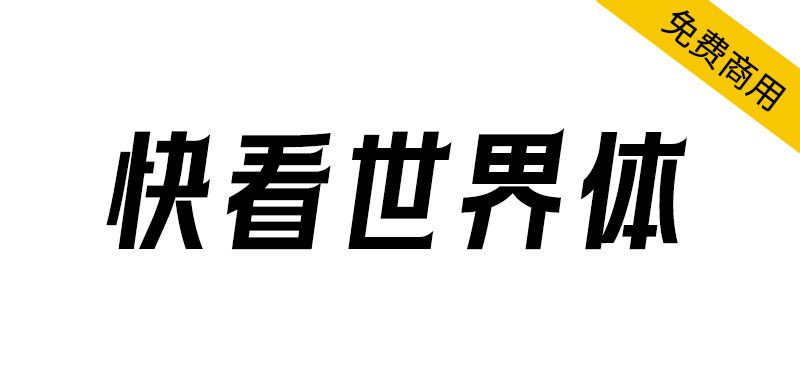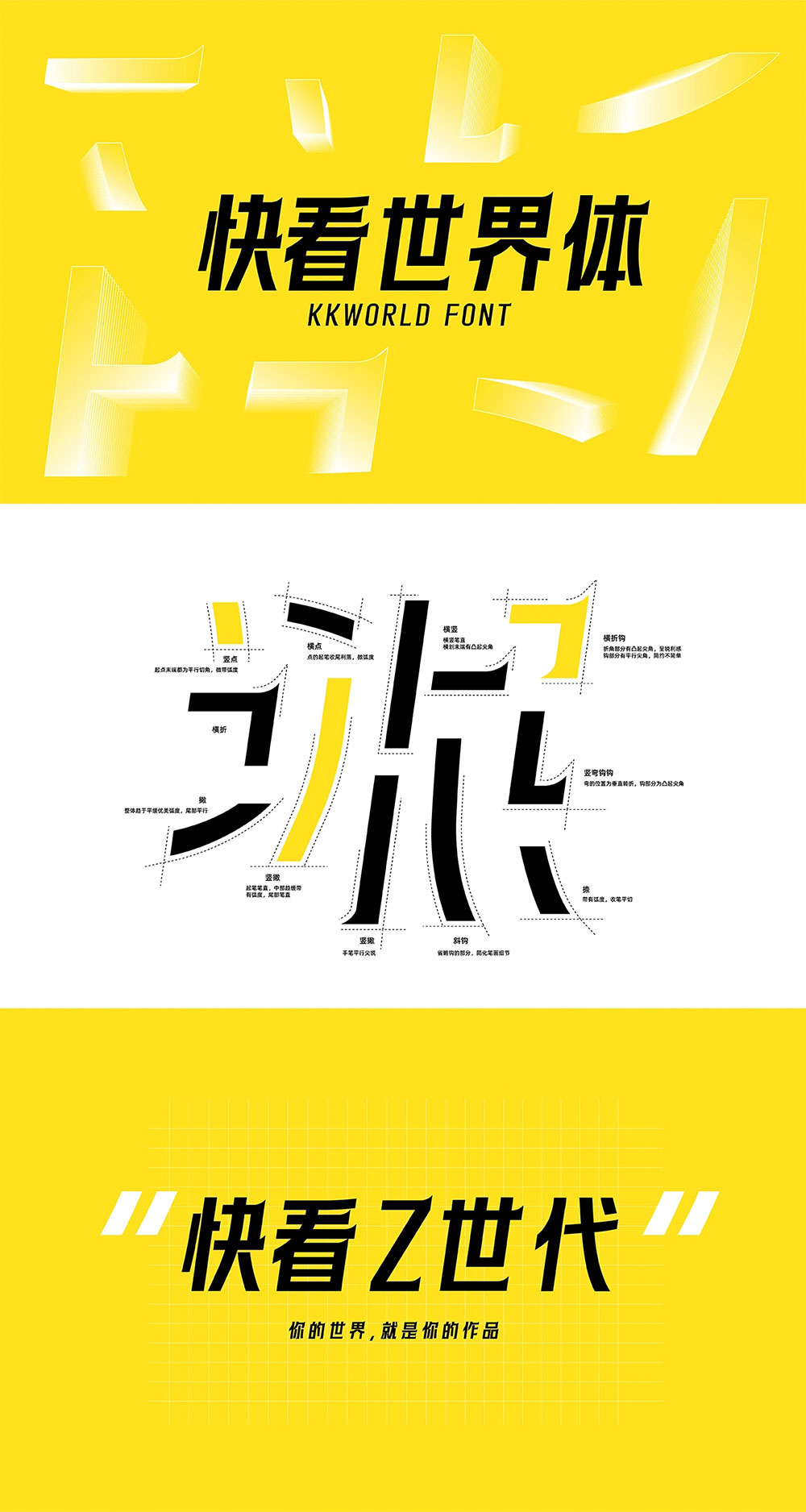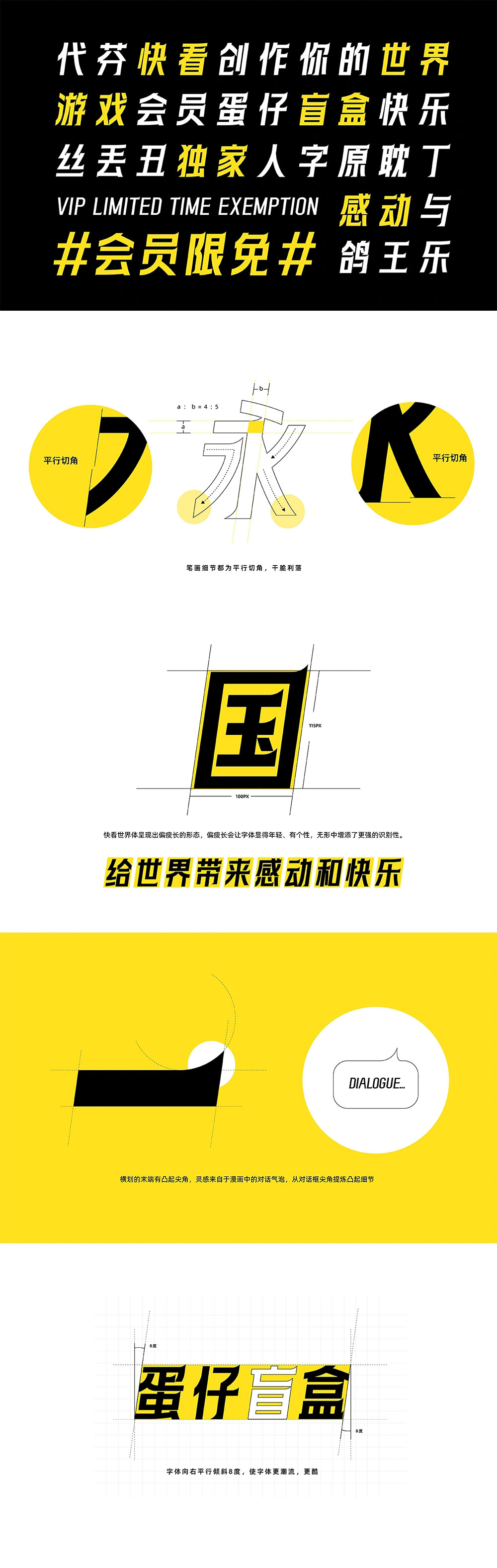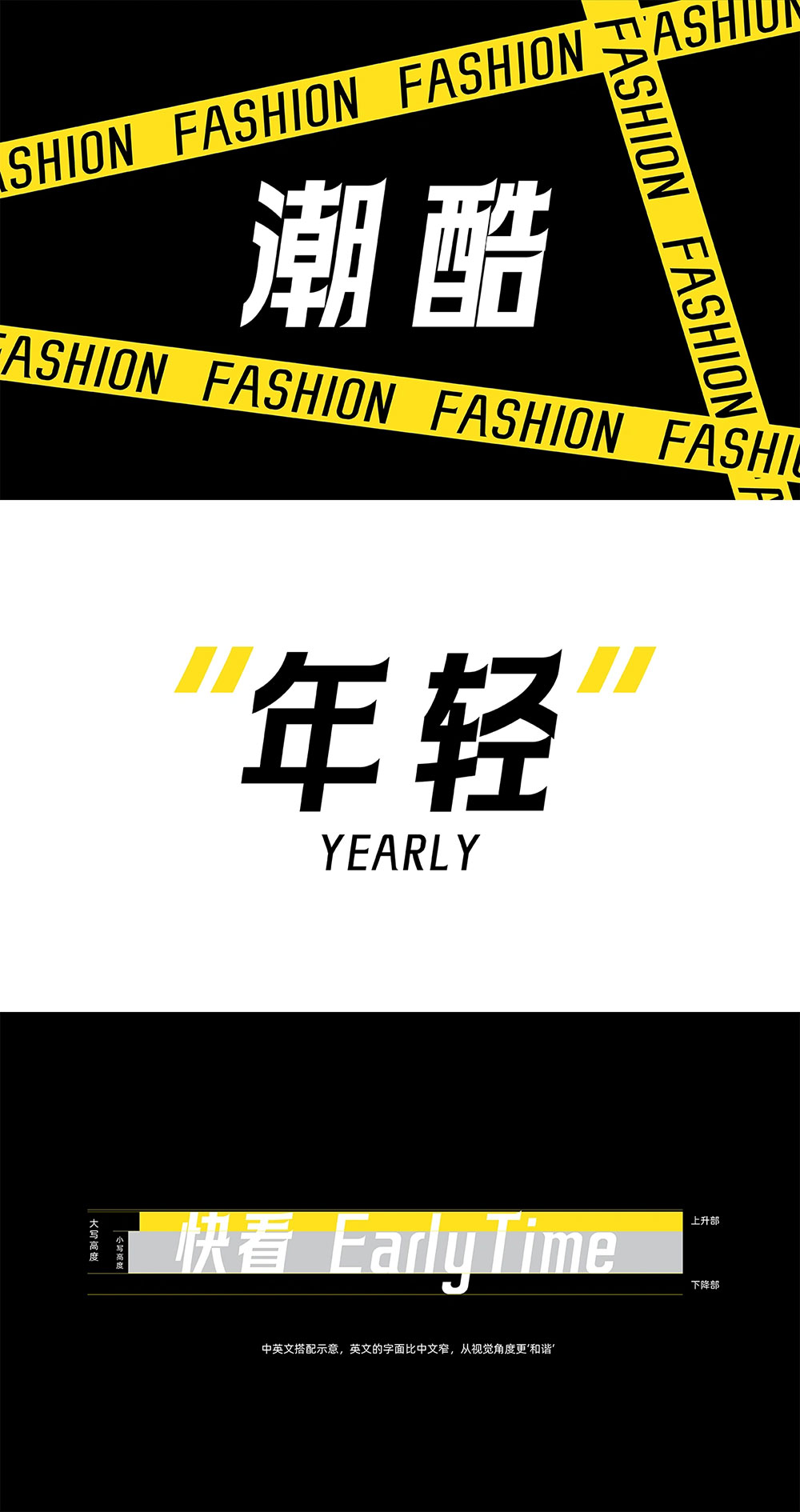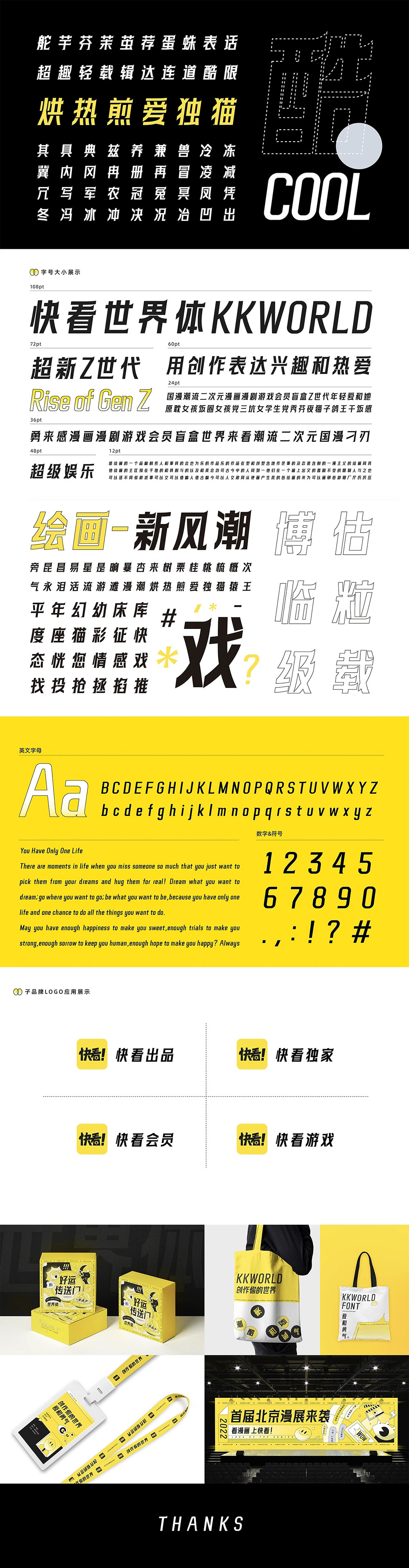
这款字是我第一款从设计-封装-测试全部自己完成的字库快看世界体由快看KKDC出品,字体设计以漫画中的对话框元素为起点,融入快看ACGN文化,年轻潮流,大胆有态度。
字体特点末端尖角,中宫外扩、字面瘦长、倾斜8度;包含3501个字。现应用于快看品牌营销、漫展、内部企业文化宣传、客户端等场景。免费授权全社会使用(包括商用)